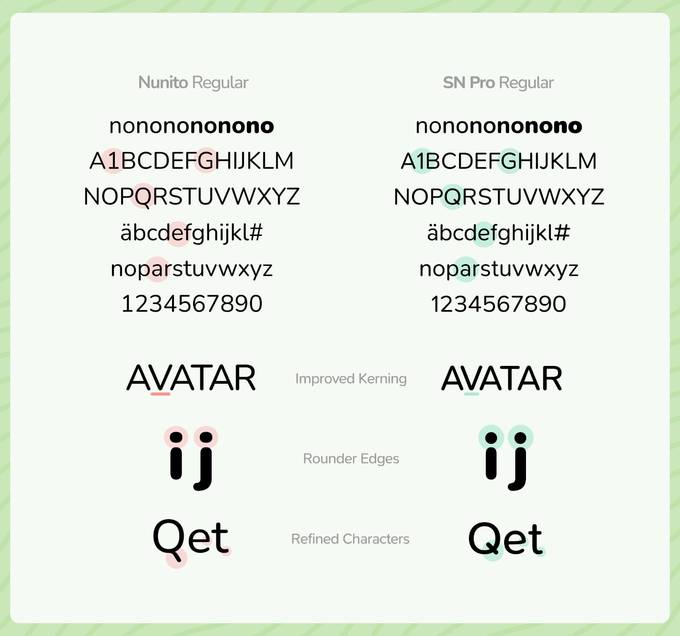
优设标题黑
免费强烈推荐!全网下载量高达590W次
得意黑
免费微笑的嘴角!超优质开源美术字体
优设好身体
免费实用!覆盖绝大多数的设计场景
优设字由棒棒体
免费集可爱俏皮为一体的专业美术标题字
优设鲨鱼菲特健康体
免费强烈推荐!覆盖大多数电商应用场景
优设标题圆
免费标题黑的升级版,使用范围更广
抖音美好体
免费字节跳动出品免费可商用中文字体
武汉英雄体
免费宝藏新字!写满武汉精神的英雄字体
快看世界体
免费快看出品,年轻潮流、漫画感的中文字体
思源黑体
免费可变版!超多人喜爱的开源字体
阿里巴巴普惠体2.0
免费222841个字符,覆盖全球175个语种
钉钉进步体
免费推荐!充满科技活力专为标题场景而生
瀞之库格尔黑体
免费左扁右宽!基于思源黑体魔改的日文字体
荣耀字体HONOR Sans
免费业界首款字重和中宫双重无极可变的字体
演示斜黑体
免费速度感!Keynote 可用的中文倾斜字体
字体圈伟君黑
免费三种字重!沉稳中正的规范黑体字体
更纱黑体
免费规正!为代码编辑优化的等宽字体
标小智无界黑
免费扁平粗厚,酷帅的超粗黑体
阿里妈妈数黑体
免费人机协同设计,高效解决电商用字需求
文泉驿正黑
免费适用范围广!有特色的电脑黑体字体
OPPO Sans
免费超多细节!5种字重的全球化品牌字体
vivo Sans
免费简洁易读!自然舒适阅读体验的现代黑体
文道潮黑体
免费适用性极高!有潮流感的风格化黑体
HarmonyOS Sans
免费为鸿蒙系统设计的全新系统默认字体
汉字拼音体
免费推荐!非常适合教育类设计中使用
联盟起艺卢帅正锐黑体
免费字形厚重有力的创意中文字体
霞鹜新晰黑
免费基于IPAex黑体的中文开源字体
江城正义体
免费削减横笔粗细,字体看上去更具现代感
德拉黑体
免费力量感十足的免费开源日文字体
超极细
免费极细的透明感现代清爽字体
未来荧黑
免费多重字重,造型简明现代,效果清新轻快
寒蝉活黑体
免费模拟油墨溢出效果,斑驳印刷感的黑体
Plix普力士
免费人文风!适用潮流艺术场景的现代黑体
思源宋体
免费4种语言7个字重的文学性衬线体
万事全兴体
免费视觉冲击力强!适用于电商促销等强传播场景
猫啃网风雅宋
免费笔挺优雅!基于思源宋体改造的中文字体
寒蝉端黑宋
免费硬朗雅致!免费可商用开源中文字体
狮尾肉丸体
免费超大字符集,游走于古典与可爱之间
狮尾四季春
免费清新轻快!简明现代化版面效果的字体
花园明朝体
免费推荐!涵盖几乎所有汉字字形的日文字体
华光俊秀体
免费纤细修长,应用范围广泛的中文字体
萌神拼音体
免费用于学习教育类中文拼音印刷字体
飞花宋体
免费秀气雅致!收录了简体6763个汉字
源界明朝体
免费散发着一种古老破碎的感觉
台湾明体
免费古朴大方美观的中文字体
字体圈欣意吉祥宋
免费圆润平滑古风韵味的宋体标题字
一点明体
免费标准制作!传承汉字构字的科学系统
装甲明朝体
免费硬朗阳刚的可商用日文字体
香萃打字机体
免费人工精调!模仿打字机洇墨效果
鼎猎宋刻体
免费版式雅洁!适合餐饮、美妆等行业
月星楷
免费常见于书法字贴!古体字形风格开源中文字体
阿里妈妈东方大楷
免费现代传统结合,字形丰腴厚重而饱满
演示悠然小楷
免费拙朴感的书法字体,对阅读识别友好
方正楷体
免费方正出品,笔画圆润柔和的楷体
江西拙楷体
免费黄煜臣创作的拥有自然美感的手写楷体
庞门正道真贵楷体
免费推荐!粗细适中特点鲜明的书法字体
演示夏行楷
免费半自动流程字稿制作!流畅平滑流动舒展的书法字体
就是不错字
免费能自动纠错的开源繁体中文字
汇文正楷
免费雅致复古!字体结构硬朗的正楷字体
猫啃硬笔楷书
免费硬笔楷书!适用于各种手写场合
猫啃忘形圆
免费线条流畅!兼具设计感与可读性
寒蝉半圆体
免费观感舒适!应用范围广的中文圆体字
阿里健康体
免费首套中文&盲文&注音的定制字体
阿里妈妈方圆体
免费国内外为数不多的双轴可变中文字体
荆南麦圆体
免费圆润饱满,可爱萌系风手写中文字体
江城圆体
免费拐角圆润平滑,适合国内设计师使用
江城知音体
免费灵气柔美三个字重的中文字体
仓耳舒圆体
免费圆润饱满五个字重,应用范围较广
猫啃网糖圆体
免费国内首款免费商用的传统圆体字形
资源圆体
免费7种字重,对简体字体的支持较好
小衫圆体
免费极具美观和可读性的哥特式圆形设计
Open粉圆字体
免费针对中文日常应用优化的开源字型
源泉圆体
免费推荐!正统开源圆体字体
俊羽圆体
免费圆润规整,通过程序自动产生多种字重
Zen圆体
免费5款字样!圆润可爱的中文字体
阿瓜准圆体
免费字形方正圆润等粗英文字体
智勇大同体
免费AI辅助!传统与现代完美融合的手写字体
辰宇落雁体
免费太好看了!充满温度的书写手感字体
刘欢卡通手书
免费糅合了传统意味的现代标题字体
可爱少女体
免费青春甜美,俏皮优雅的少女气质的字体
萌神手写体
免费汉语拼音标注!更快地学习和阅读汉语
今年也要加油鸭
免费稚嫩萌趣!简约硬笔手写风格字体
内海字体
免费稚气灵巧,可爱手写少女字型
杨任东竹石体
免费推荐!7种字重的可商用手写体
小可奶酪体
免费推荐!可爱趣味风格的手写体
荆南麦圆体
免费圆润饱满,可爱萌系风手写中文字体
日本濑户可爱风
免费设计师手书创作!亲和力很强
手书体
免费推荐!非常像我们日常手写的字
沐瑶软笔手写体
免费手写痕迹,字体可爱风趣不失活泼
沐瑶随心手写体
免费以女儿名字命名,随心书写的手写字体
851手写杂书体
免费圆珠笔效果!自然轻松可爱灵活的日文字体
新叶念体
免费温柔圆润人文气息的中文手写字体
清松手写体
免费休闲可爱三种款式的手写字体
梅干手写体
免费可爱休闲易于阅读的手写字体
拾陆字濑户2.0
免费活泼可爱字库超全的中文字体
寒蝉手拙体
免费笔画流畅洒脱的手写体
贤二体
免费诙谐幽默的手写字体字体
悠哉字体
免费整洁干净!透露出文艺娴静的感觉,适用范围较广
重庆山城棒棒体
免费中国风字体!适用于电商文创等不同领域
云峰飞云体
免费广泛用于平面设计、影视、海报等行业的毛笔中文字体
衡山毛笔行书
免费日本书法家青柳衡山挥毫写成的毛笔字体
钟齐志莽行书
免费以韦志莽毛笔书法开发而成书法字体
Aa剑豪体
免费推荐!字符超7000个中文手写字体
龚帆免费体
免费笔触明显!3000+常用简体字
仓耳周珂正大榜书
免费推荐!适用全领域的书法艺术字体
正风毛笔字体
免费基于衡山毛笔行书增补的毛笔字体
庞门正道粗书体
免费简洁有力风格百搭的书法字体
演示佛系体
免费纪国才先生手写古典书法字体
演示秋鸿楷
免费推荐!曲折有力厚重质朴的书法字体
黄令东齐伋体
免费复古!极富人文气息的书法字体
演示春风楷
免费半自动流程字稿制作的书法字体
飞波正点体
免费适用于标题大字排版的毛笔字体
鸿雷板书简体
免费鸿雷老师手写!极具古风古韵的手写字体
美呗嘿嘿体
免费简朴大方!庄重有力的中文字体
字魂扁桃体
免费喇叭口的设计,让微笑弧度卷起来
Aa厚底黑
免费好用!兼具厚重与活泼感的标题字体
Typefesse
免费Typographica 年度最受欢迎的字体
猫啃网故障黑
免费炫酷的故障风格科幻艺术黑体字
字体传奇雪家黑
免费模仿雪花!复古气息的中文黑体
托加里特体
免费7 种字重的机甲魔幻风格子实体
黑蔷薇灰姑娘体
免费充满魔幻神秘且特立独行的艺术字体
明达明达无锋体
免费效果出色!舒展圆润的开源中文字体
铁蒺藜体
免费收录超1万字!个性十足的中文字体
像素Silver
免费推荐!独具特色适合游戏的像素字体
Unifont点阵黑
免费超5.5万符号,字符超全的像素字体
站酷小薇LOGO体
免费个性鲜明!创新前卫的中文字体
庞门正道轻松体
免费笔画粗细对比,灵动活泼文艺字体
字体传奇特战体
免费6763个汉字,严谨规整的创意字体
江城尖刃黑
免费尖锐锋利,字体具有更好的辨识度
阿朱泡泡体
免费可爱!像极了小孩子随手画的泡泡
点点像素体
免费像素黑体!三种形态风格百搭
中文像素字体
免费经典复古风格独特的中文字体
峰广明锐体
免费明朗锋锐挺拔端正的中文字体
站酷庆科黄油体
免费复古又时尚的中文标题字
胡晓波男神体
免费简介大方,字体稳重高挑适用性强
汇文港黑
免费怀旧风!香港广泛使用的港版岩田黑体
标小智龙珠体
免费圆点点缀的俏皮可爱卡通字体
荆南俊俊体
免费可爱!活泼、卡通的中文字体
猫啃什锦黑
免费活泼有趣!可爱马克笔手绘风格字体
宅在家粉條甜
免费圆滑Q弹!小巧可爱的艺术字体
荆南波波黑
免费曲线流畅!俏皮可爱的卡通标题字体
麦克笔手绘体
免费马克笔手写出来的效果类似
胖胖猪肉体
免费可爱柔和日系百搭的字体
仓耳小丸子
免费活泼可爱对比夸张的中文字体
开源免费的新西文字体:SN Pro
周刊收录该字体是笔记工具 Supernotes 设计的开源且免费供个人和商业使用的新字体,SN Pro 是基于Nunito,这是一种由 Vernon Adams 设计的出色的圆形字体。SN Pro 重新设计了每个字符,改进了对 Markdown 和连字的支持。 https://supernotes.app/open-source/sn-pro/
字体删除线背后的信息:从删除线到默默无闻 MVAR
周刊收录原文:https://fenx.work/from-strikeout-to-obscure-mvar-table/ 苹方和 SF Pro 都是界面设计时常用的字体。在 Figma 中添加删除线样式时,上图中可以看到苹方和 SF 字体的删除线位置不一,一个偏下一个居中。 原因是,删除线属性由字体内的信息 OS/2 表内两个参数控制: yStrikeoutPo